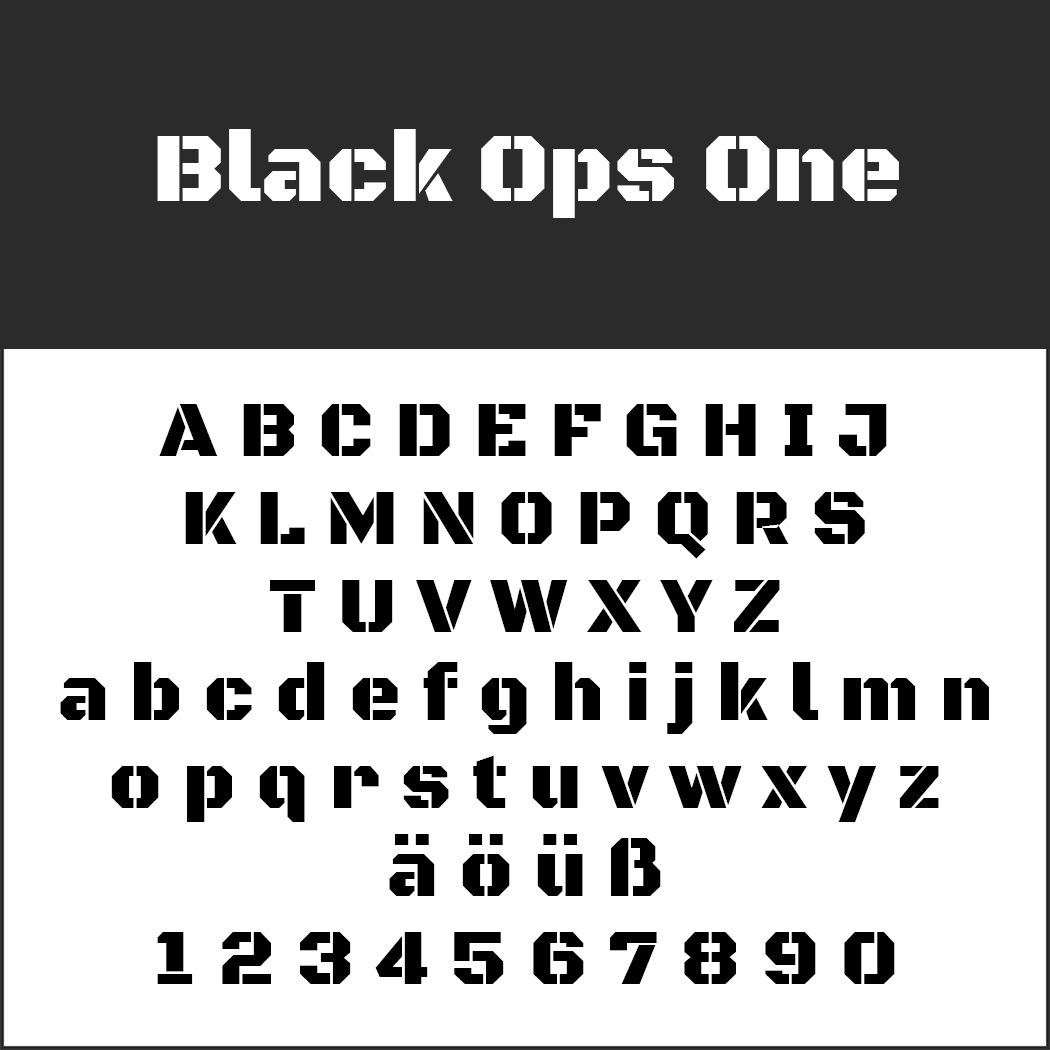
Sie passt nicht überall, aber wo sie passt, macht sie immer einen mächtigen Eindruck: die Schriftart Schablone oder Stencil, wie sie auf Englisch heißt. Nur für einzelne Schlagwörter richtig geeignet, wirkt sie vor allem auf Plakaten und als Beschriftung von größeren Behältern.
Awery
Der Schablonencharakter tritt angesichts der schwungvollen Eleganz des Fonts etwas in den Hintergrund und wirkt hauptsächlich bei den Versalien. Eine der wenigen Stencil-Schriften mit Serifen.
Black Ops One
Die kontrastarme, halbgeometrische Schrift hat ihr Vorbild in militärischen Schablonenschnitten und macht sich am besten in großen Schriftgrößen.
Capture it
Capture it wirkt wie ein Aufdruck einer in die Jahre gekommenen Kiste. Wer den Font lieber ohne „Gebrauchsspuren“ mag, findet in Cleanwork von Magique Fonts die „saubere“ Variante.
Gunplay
Für diesen aufgeräumten und schnörkellosen Font ließ sich Raymond Larabie vom Filmplakat von The Getaway mit Ali MacGraw und Steve McQueen Ali MacGraw inspirieren.
Keania One
Die Designerin orientierte sich mit ihrem Schablonen-Font an den Schriftzügen an Geschäften und Ständen in Kenia. Nach ihr „spielen die Formen mit scharfen und weichen Ecken und erzeugen ein rhythmisches Muster aus Schwarz und Weiß“.
Kenyan Coffee Stencil
Kenyan Coffee Stencil basiert auf der gleichnamigen Schrift aus den 1990er Jahren. Charakteristisch ist das schmale Schriftbild.
Marsh
Der Desginer belebte mit diesem Font eine Schrift des US-amerikanischen Unternehmens MARSH Stencil Machines wieder, die dieses während des Zweiten Weltkriegs nutzte.
Saira Stencil One
Das Omnibus-Type-Team präsentiert die Stencil-Version seines universell einsetzbaren Sans-Serif-Fonts Saira. Die Schrift wirkt trotz des Schablonencharatkers harmonisch.
Sirin Stencil
Sirin Stencil ist zwar für eine große Schriftgröße optimiert, funktioniert aber auch in kleineren Schriftgrößen sehr gut. Der besondere Clou ist der optische 3D-Effekt.
Stardos Stencil
Mit Stardos Stencil hat der Designer eine Serifenschrift schabloniert, die hauptsächlich für Anzeigen gedacht und für Bildschirme optimiert ist.
WC Wunderbach Rough BTA
Hemdsärmelig und erfrischend kommt dieser Font daher. Denn WC Wunderbach sieht so aus, als hätte man die Freiflächen in der Schablone von Hand ausgekritzelt.